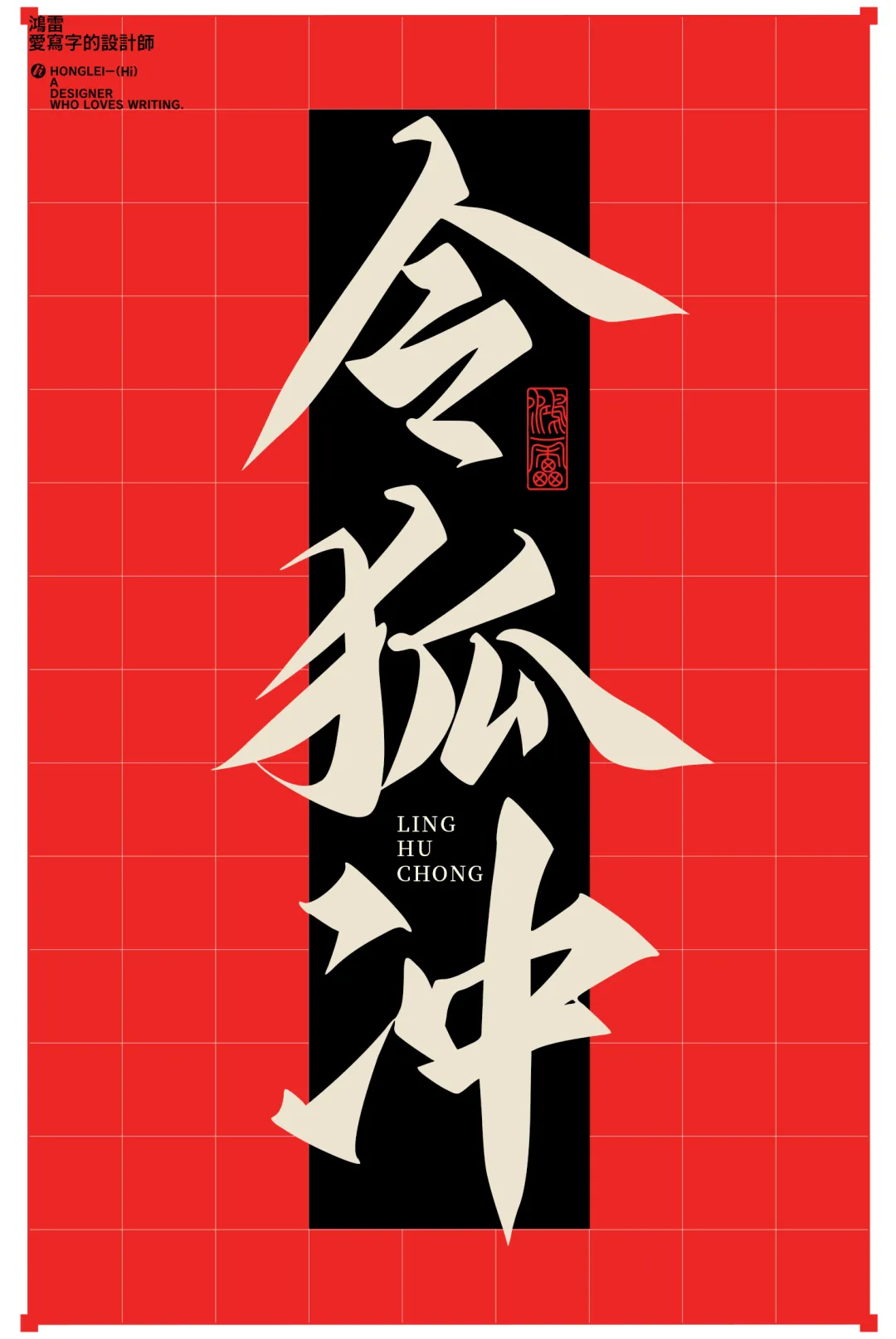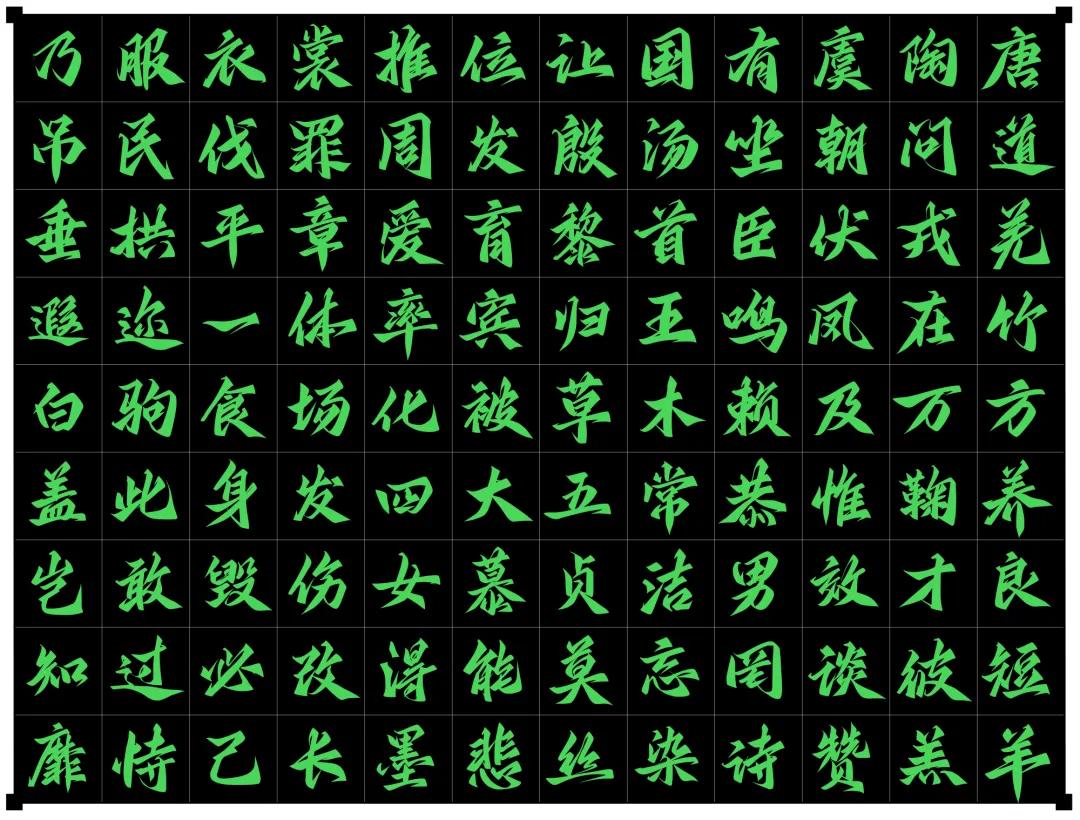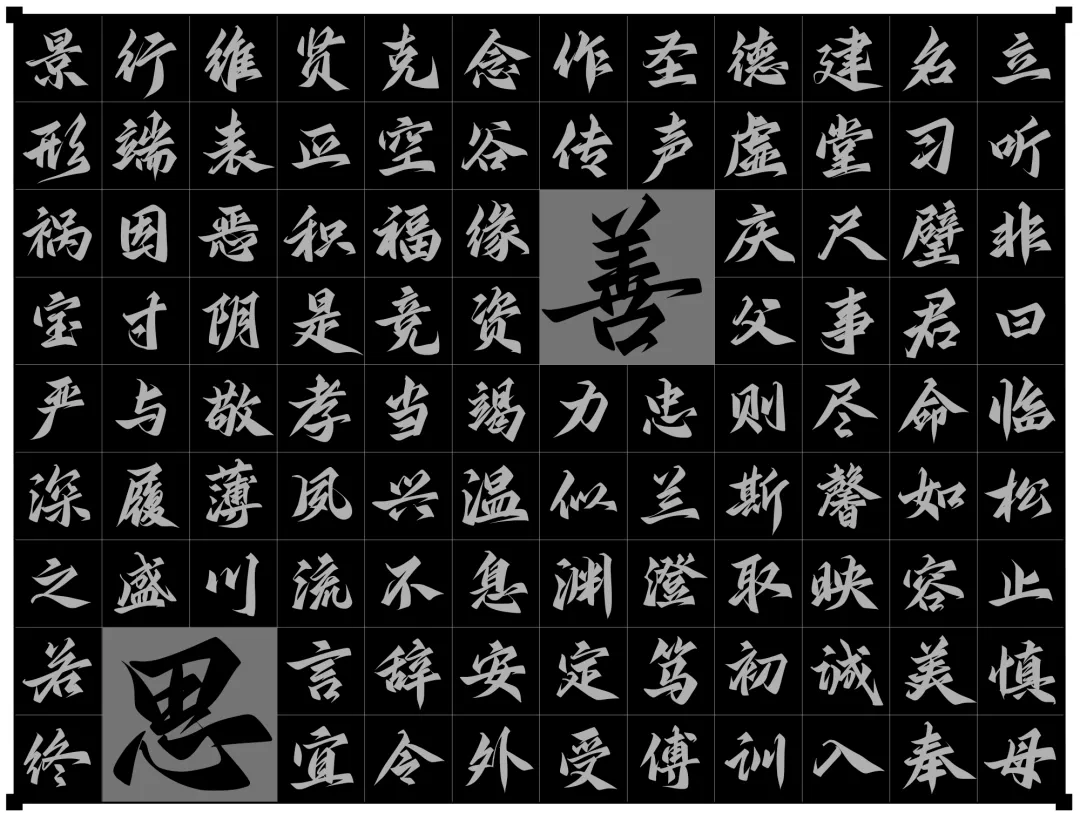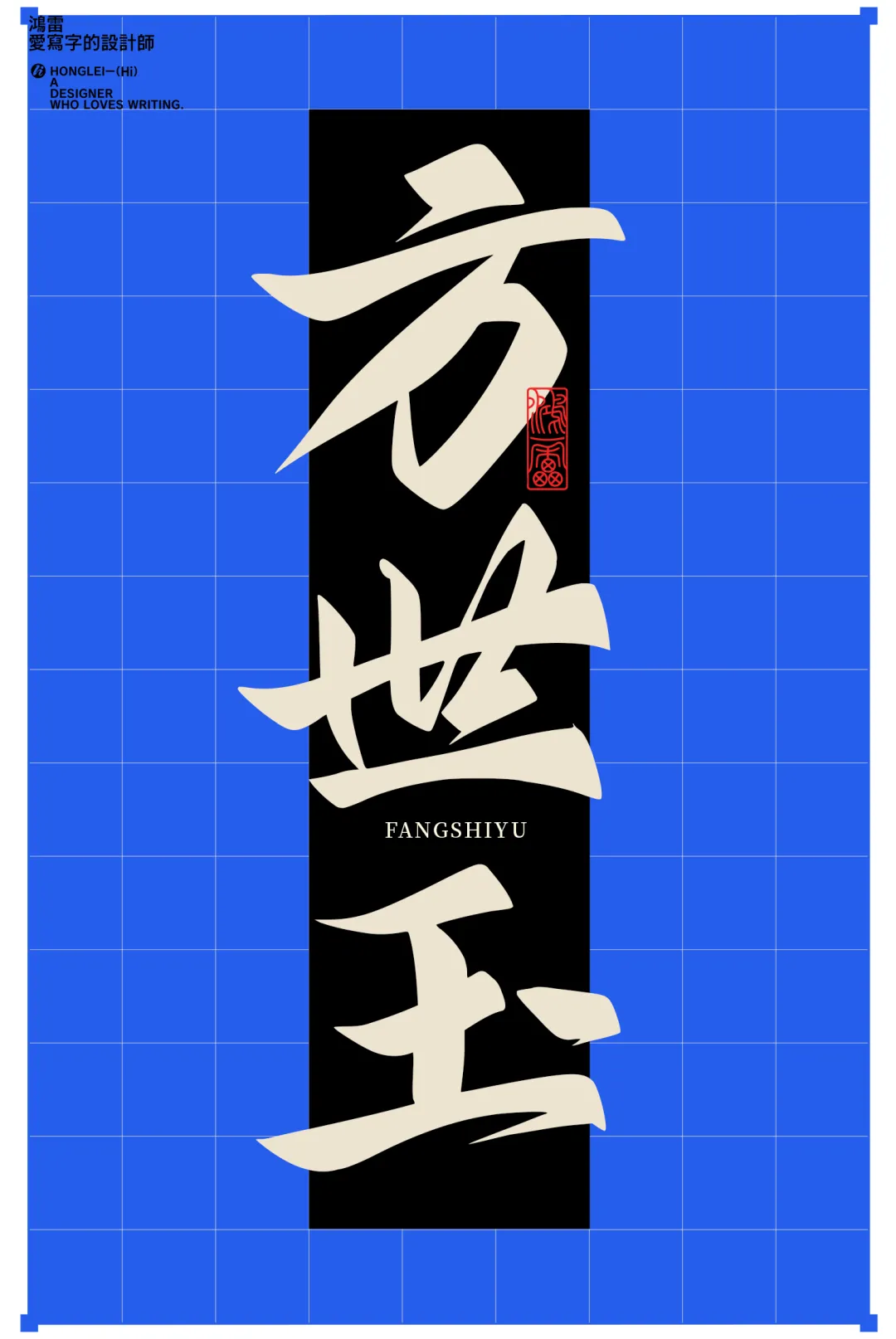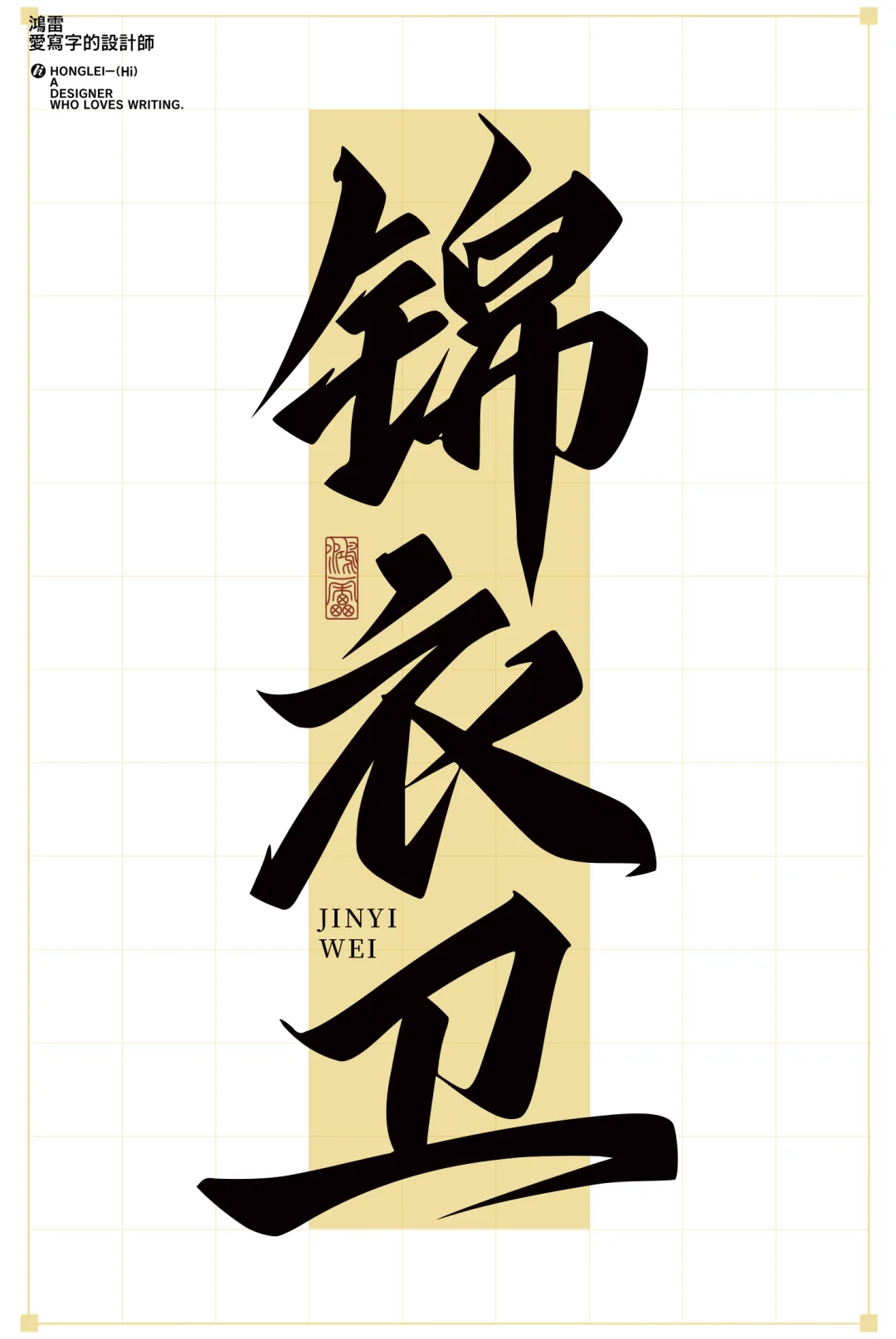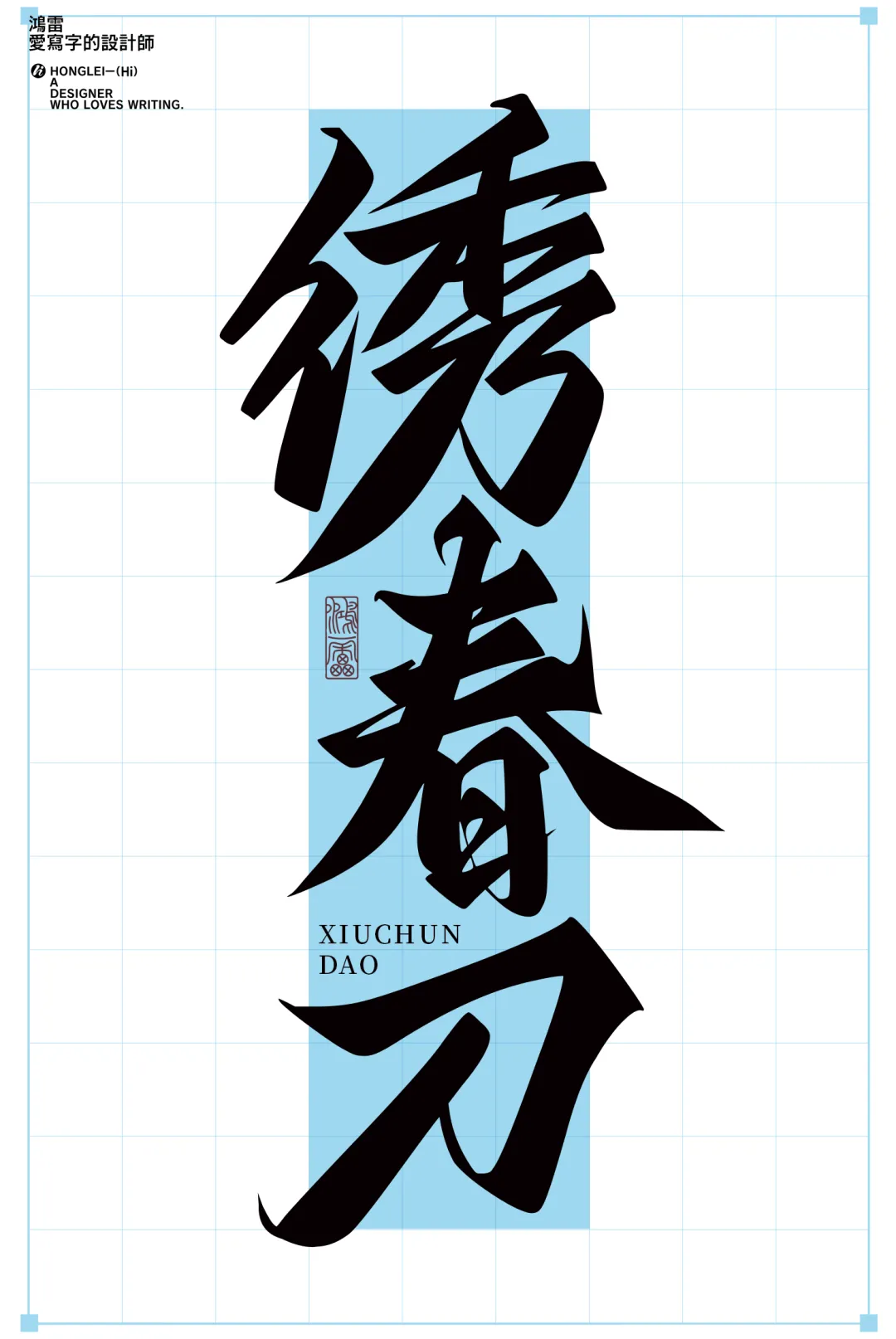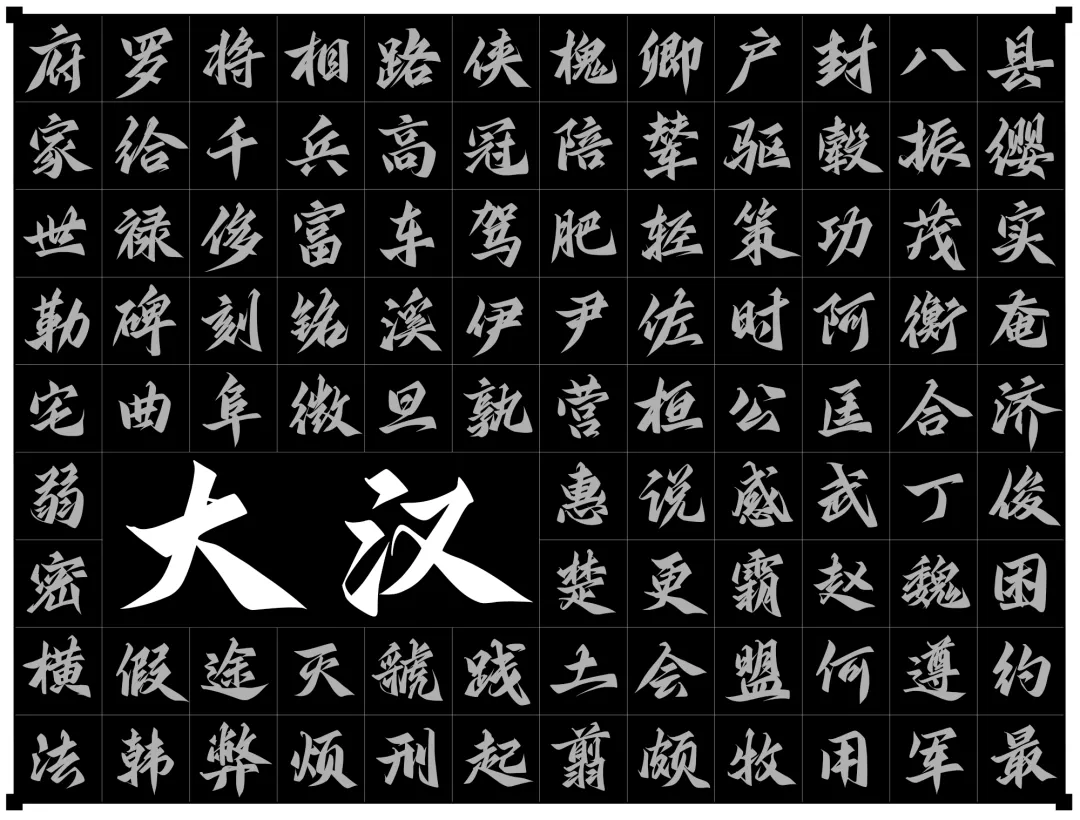
《鸿雷江湖简体》上线啦,一笔一划皆是侠气。
每个人心中的江湖
每个武侠爱好者心里,都藏着一片独属于自己的江湖 —— 没有现实琐碎,只剩快意恩仇的浪漫。
有人的江湖,藏在细节里。是腰间剑穗随风轻晃,藏着 "一剑霜寒十四州" 的潇洒;是粗陶酒壶仰头即饮,饮出 "相逢意气为君饮" 的洒脱;是旧布袍裹着 "事了拂衣去" 的低调。
有人的江湖,活在对决中。幽深竹林里,两人相对而立,剑未出鞘已带 "十步杀一人" 的张力;月下桥头,胜负分后只道 "今日承让",尽显江湖气度。
有人的江湖,重在情分。路见不平便抱 "虽千万人吾往矣" 的勇气;与知己闯难关,默契如高山流水;更敬 "侠之大者,为国为民",愿为苍生赴险。
这片江湖从不被定义,但本质不变:是对坦荡自由的向往,是心底不灭的英雄梦。正如 "人就是江湖",它永远是想起就热血的情怀。
一、鸿雷江湖简体介绍 JIANGHUZITIJIESHAO
藏在字里的江湖一笔一画皆是侠气
每个热爱武侠的人,心里都藏着一个江湖 —— 是剑穗翻飞的凌厉,是酒壶倾洒的豪迈,是竹林对决的飒爽,更是笔墨间藏不住的侠骨柔情。如今,这套字体把这份江湖气搬进了屏幕,它就是今天要介绍的 《鸿雷江湖简体》。
一笔出鞘,尽是侠气风骨
不同于市面上千篇一律的规整商务字体,《鸿雷江湖简体》从创作之初就带着与生俱来的 "江湖"气质:它的笔画起承转合间暗藏凌厉锋芒,撇捺舒展如侠客挥剑的弧度,点画落笔似暗器破空的气势。每个字形都仿佛江湖儿女的身姿 —— 既有倚剑天涯的洒脱不羁,又有行侠仗义的浩然正气,将文字的筋骨与江湖的豪迈完美交融。
笔画如剑,刚柔并济
横画似长刀劈风,利落有力;竖画如长枪立地,挺拔洒脱;偶尔带起的笔锋小勾,像极了侠客收剑时的余劲,不刻意却藏着锋芒。
字形洒脱,无拘无束
没有过度的对称与拘谨,字体略带随性倾斜,仿佛江湖浪子信手挥毫,既有 "十步杀一人" 的凌厉,也有 "醉卧云端笑人间" 的洒脱。
藏巧于中,满是武侠
部分字体的撇捺延伸如披风飘展,点画似暗器轻掷,哪怕是简单的 "江湖""侠客" 二字,都能让人联想到刀光剑影的场景,瞬间拉满武侠氛围。
二、笔画细节风格 BIHUAXIJIEFENGGE
横画:起笔顿笔如长刀出鞘蓄力,收笔回勾似剑刃收鞘余锋
竖画:挺拔如长枪立地,中段粗显沉稳,末端斜切见枪尖锐度
钩/撇捺:钩尖短促锐利如 "杀招" 收势,撇画末端轻挑如披风翻飞,捺画舒展似伸剑指路
三、应用场景预设 YINGYONGCHANGJINGYUSE
1、江湖字体词组效果
2、整体多字符展示